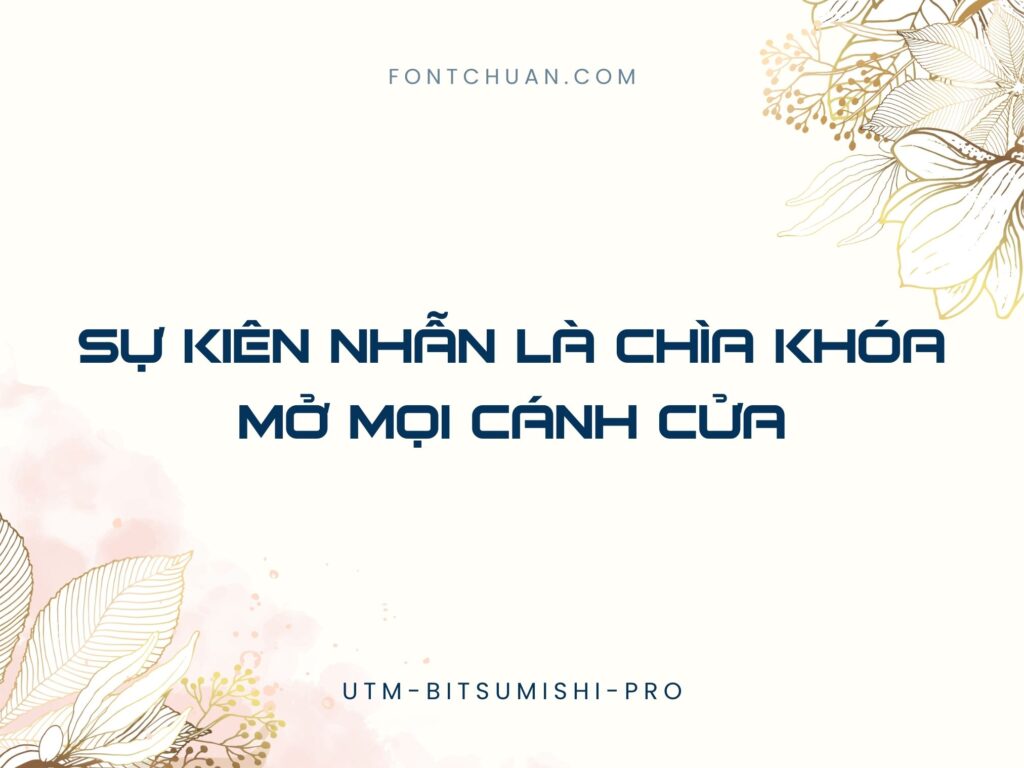
Font UTM Bitsumishi Pro Việt Hóa
UTM Bitsumishi Pro là phiên bản Việt hóa của font chữ Bitsumishi, một kiểu chữ thuộc phong cách thiết kế hiện đại, mang hơi hướng công nghệ và cấu trúc hình học sắc nét. Font nổi bật với các ký tự góc cạnh, bố cục chữ chắc chắn, tạo cảm giác tương lai và chuyên nghiệp. Phiên bản Việt hóa đã được thực hiện, hỗ trợ đầy đủ tiếng Việt cùng hơn 100 ngôn ngữ khác. Đây là một trong những font được thành viên Font Chuẩn sưu tầm và chọn lọc, nhằm phục vụ nhu cầu thiết kế hiện đại và khác biệt.
UTM Bitsumishi Pro có cấu trúc chữ vuông vức, khoảng cách chữ đều, đường nét dứt khoát và rõ ràng, rất phù hợp với các dự án thiết kế tiêu đề, nhận diện thương hiệu, bao bì sản phẩm hoặc giao diện công nghệ số. Đồng thời, font này cũng có thể được ứng dụng như một Font chữ spa, mang đến sự hiện đại nhưng vẫn tinh tế, thanh lịch cho các thương hiệu chăm sóc sức khỏe, làm đẹp và spa. Ngoài ra, những ngành nghề như quảng cáo, giáo dục, công nghệ và bất động sản vẫn có thể tận dụng UTM Bitsumishi Pro để truyền tải cảm giác mạnh mẽ, chắc chắn và hiện đại trong bố cục thiết kế.